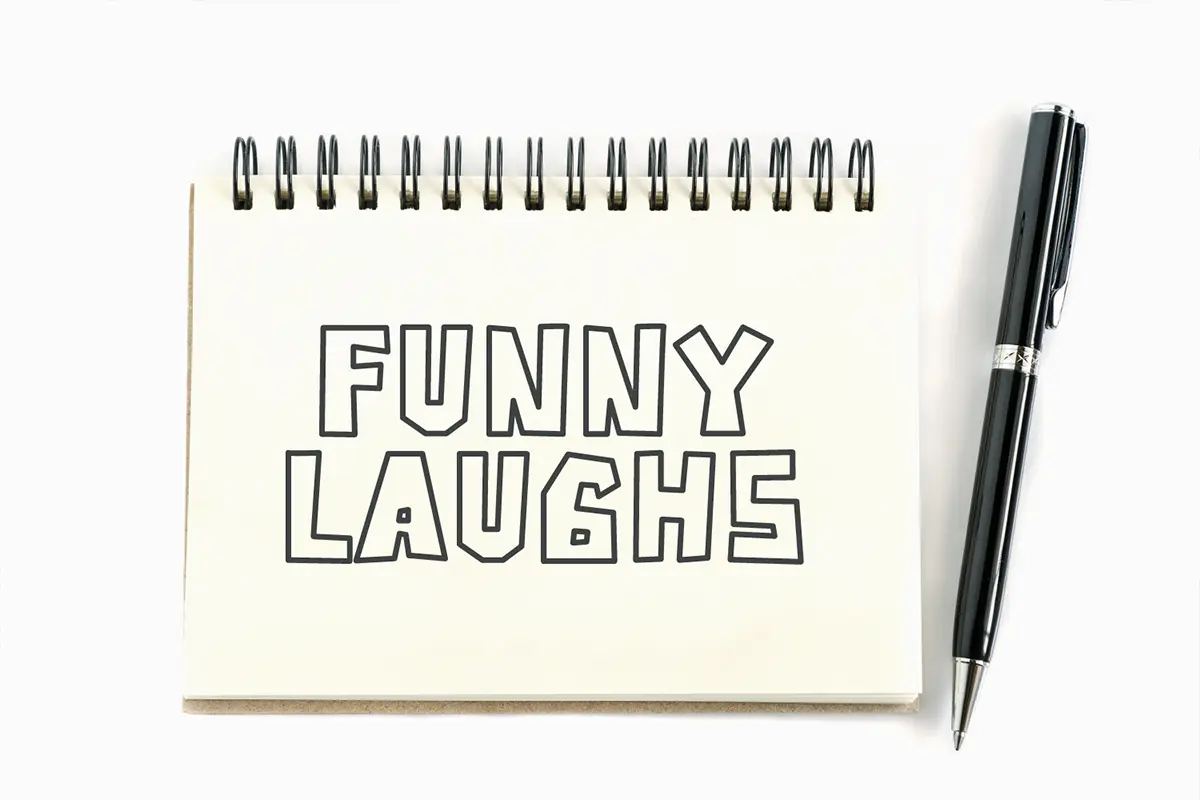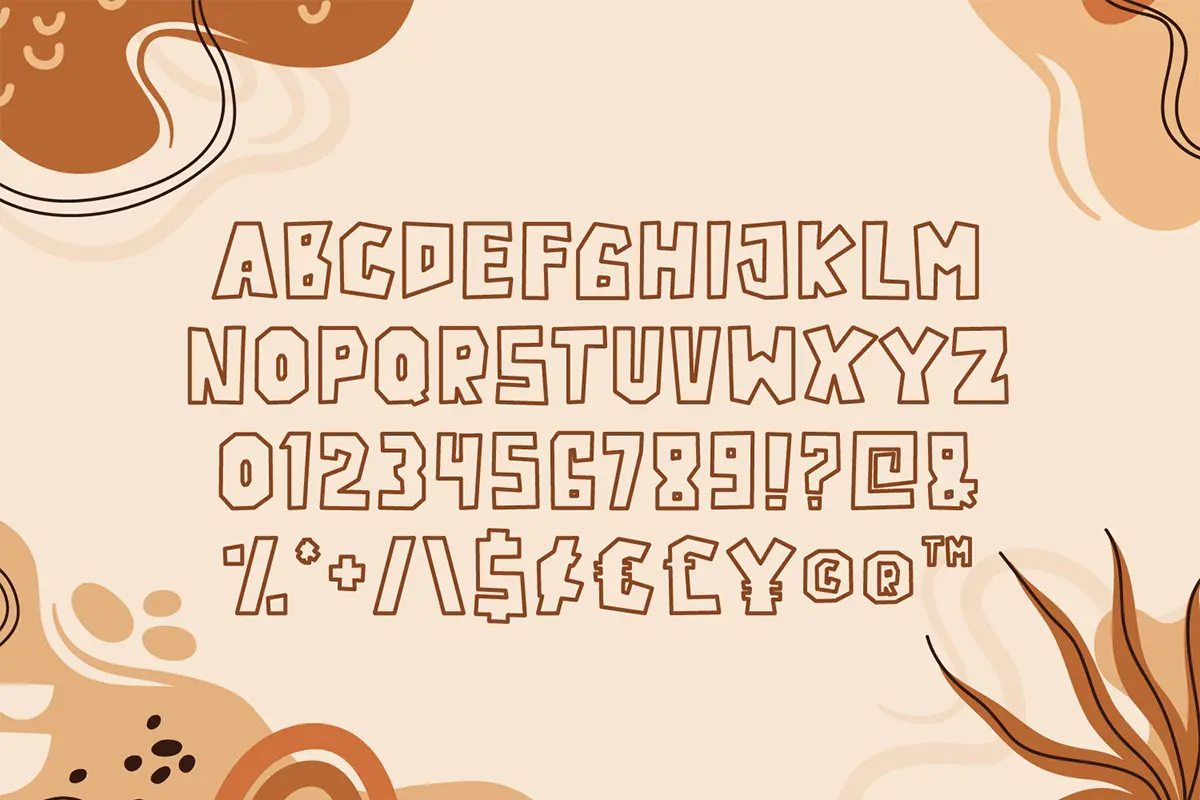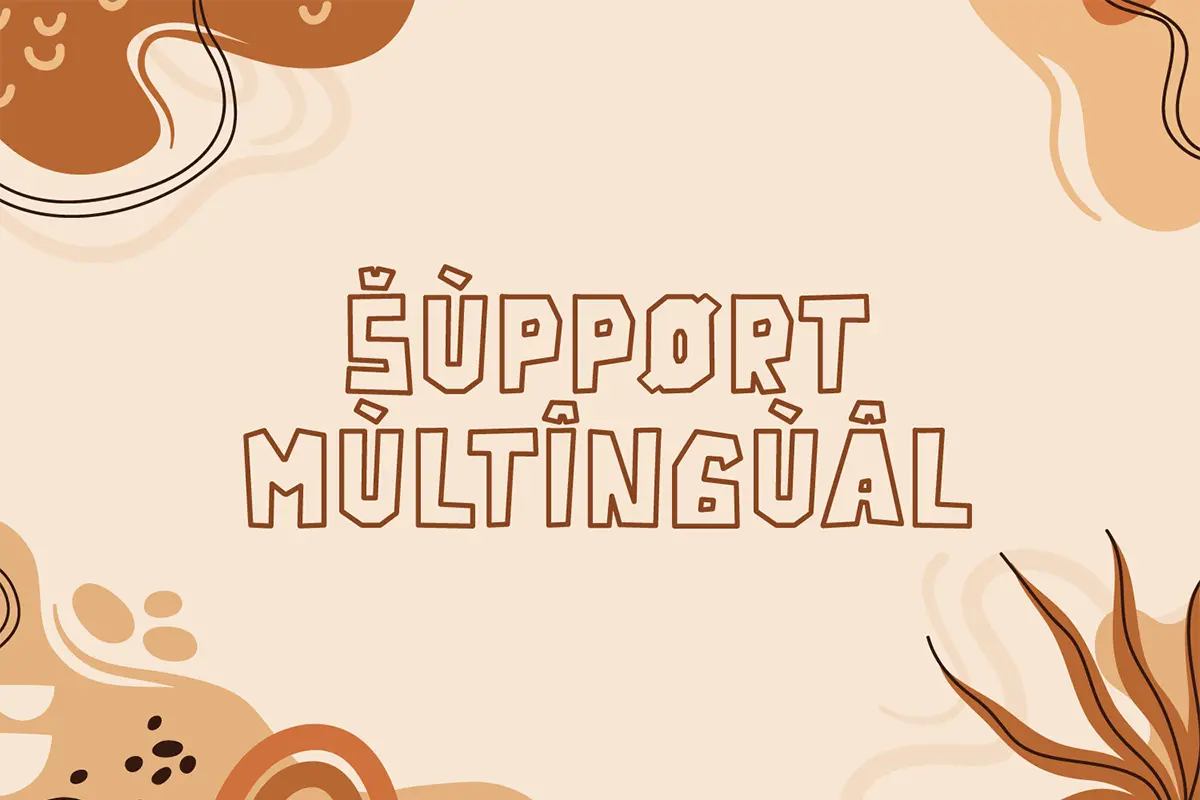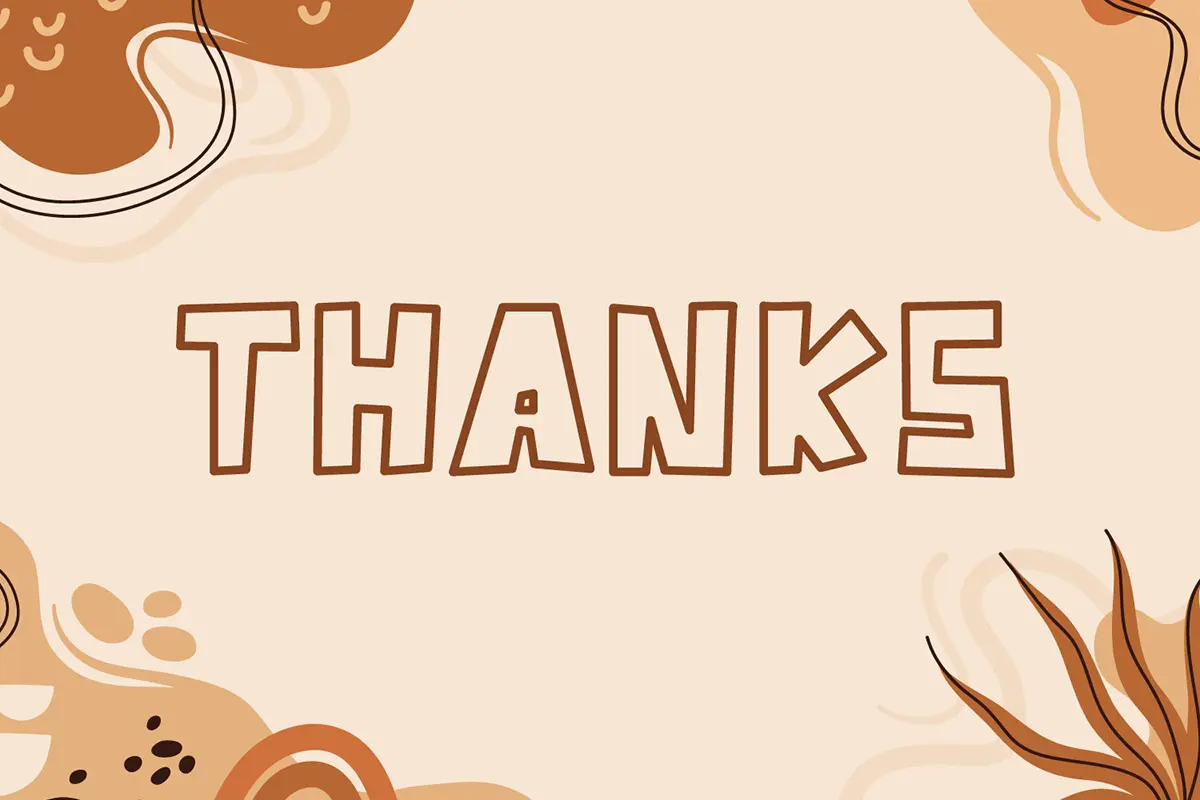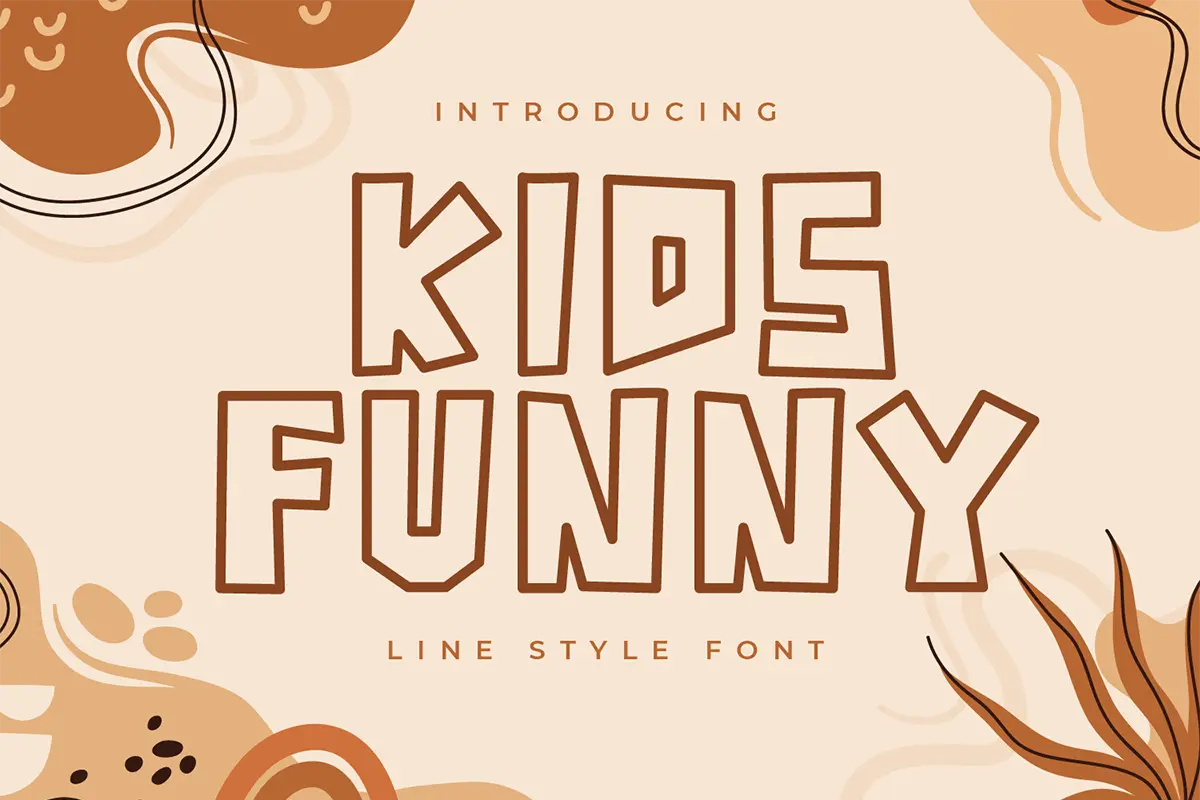
فونت نمایشی بامزه و کودکانه
فونت Kids Funny یک فونت نمایشی بامزه و دوستداشتنی است که با حالوهوای کودکانه و جذاب طراحی شده. این فونت با سبک غیررسمی و صمیمی، خوانایی بالا و جذابیت بصری، گزینهای عالی برای پروژههای خلاقانه است.
⭐ ویژگیهای محصول:
- سبک: Display Font – فونت نمایشی کودکانه و بامزه
- طراحی: کاراکترهای شاد، ساده و خوانا
- فونتی همهکاره و انعطافپذیر برای انواع پروژهها
🎯 موارد استفاده:
- طراحی کارتهای تبریک و دعوتنامههای کودکانه
- پوسترها و بنرهای سرگرمکننده و آموزشی
- بستهبندی محصولات کودک و سرگرمی
- پروژههای آموزشی و پرزنتیشنهای خلاقانه
- طراحیهای دیجیتال برای شبکههای اجتماعی